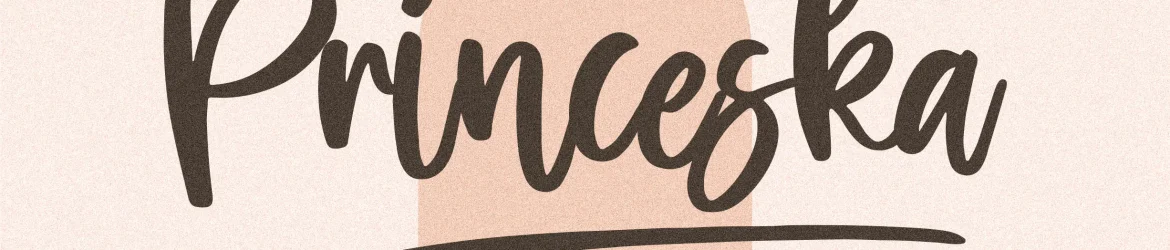
Princeska Font – Fonte Grátis
Princeska Font
A fonte Princeska é perfeita para qualquer projeto que esteja buscando uma sensação autêntica e única, seja ela um design minimalista ou mais elaborado. Através do seu estilo autoral de escrita manuscrita, a Princeska pode transformar seus projetos digitais em algo realmente especial. Seja você criando uma marca exclusiva para sua empresa, fazendo designs interiores, produzindo embalagens de produtos ou até mesmo personalizando seu próprio cupom de loja, o Princeska tem capacidade de oferecer uma expressão única que combina perfeitamente com as necessidades dos seus projetos. Além disso, a fonte é ideal para criar uma identidade visual unificada, tornando-a um recurso valioso para designers e criadores de conteúdo no mercado brasileiro, onde o cuidado detalhado em cada elemento pode fazer toda a diferença no sucesso de seu trabalho. Seja você um designer gráfico ou não, a Princeska oferece uma maneira divertida de adicionar um toque único à sua arte digitais, tornando suas criações ainda mais memoráveis e autênticas.